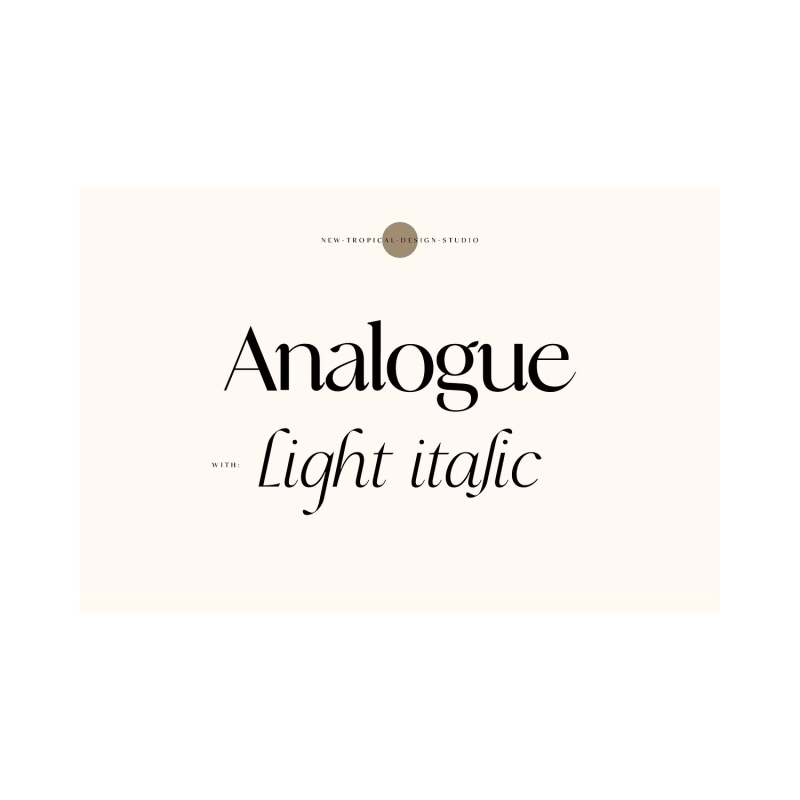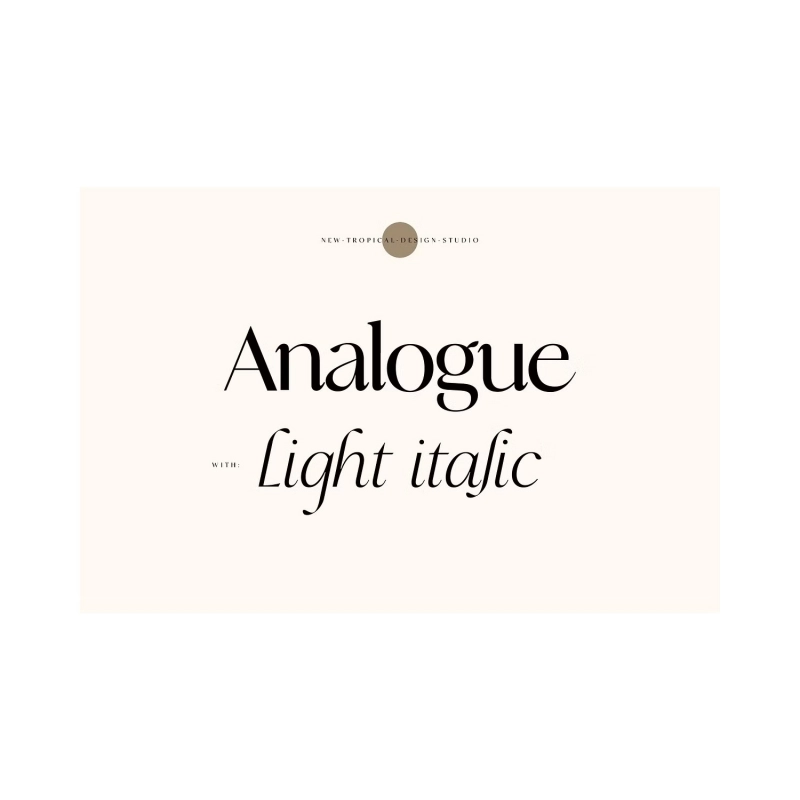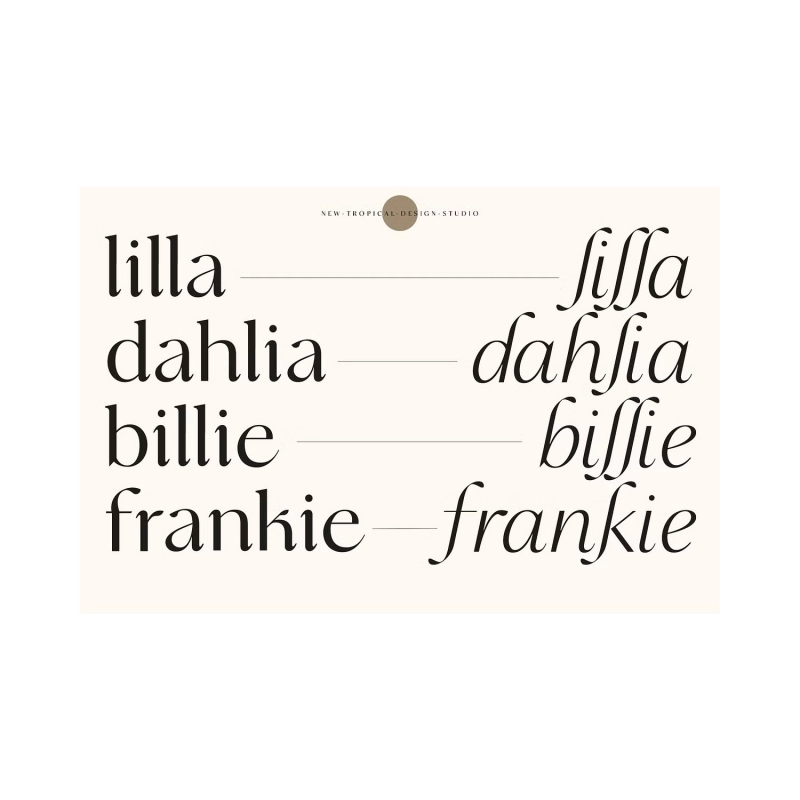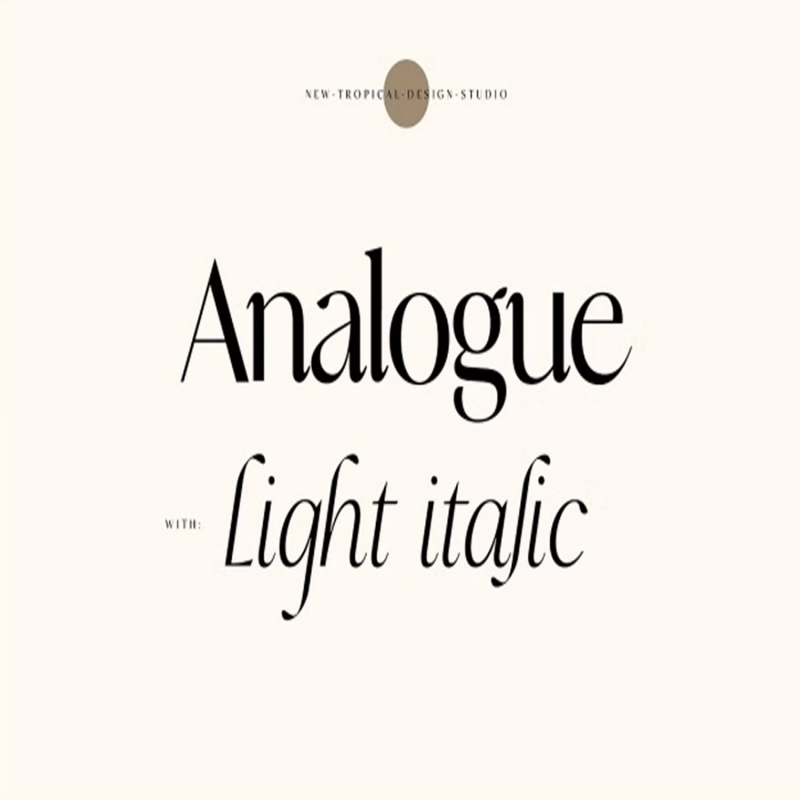
تناظري - خط عصري أنيق
التناظرية هي كل الطبقة. خط عصري أنيق هو مزيج من serif و sans serif. إنها منحنيات ناعمة ممزوجة برموز عالية التباين تضفي عليها صفات أنثوية وذكورية. مع مائل فاتح متباين ، يعمل Analogue بشكل رائع في تصميم التخطيط لعلامات الاقتباس أو نسخة الجسم. تشكل المنحنيات الأنيقة أيضا شعارا فريدا أو إعلان رئيسي. التناظرية يأتي مع دعم متعدد اللغات أيضا.
• وشملت نمط مائل كامل أيضا.